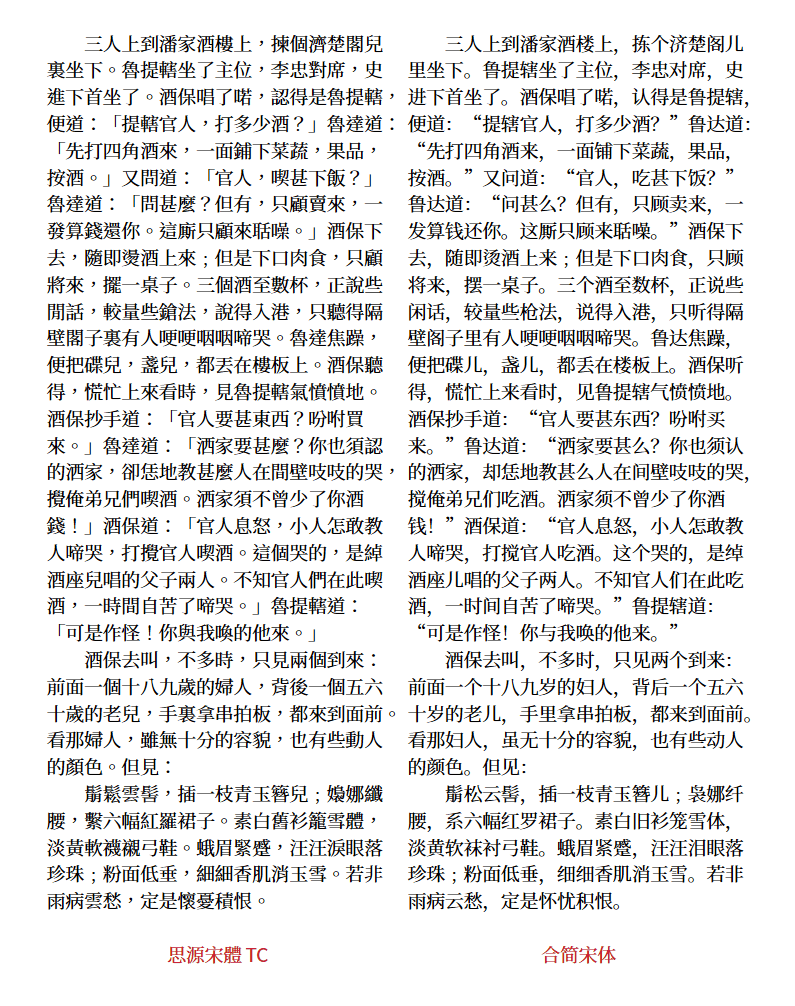
HeSimpl Serif 合简宋体
HeSimpl Fonts 是一套基于思源黑体与思源宋体(简体版)开发的繁简转换字体。
该字体能够将繁体内容自动转换为简体,并深度利用 OpenType 技术特性,实现了基于上下文的“一繁多简”动态匹配功能,显著提升了繁简转换的精准度。
字体特性
1. 包含字族
- HeSimpl Sans (合简黑体)
- HeSimpl Serif (合简宋体)
2. 优势
- 动态化匹配:借助 OpenType 特性,字体能够自动在多个简体候选字中选择最准确的一个(如“乾坤”对应“乾坤”、“乾燥”对应“干燥”)。
- CJK 大字库:继承了思源系列极广的字符覆盖率,确保在处理复杂 CJK 文本时几乎无缺字困扰。
效果预览
以下对比图展示了繁体文本的呈现效果:
对比说明: 下图中左侧为 思源宋体,右侧为 合简宋体。
预览文本全部为繁体,取自《水滸全傳》第三回,重点展示了本字体对繁转简的自动转换效果。